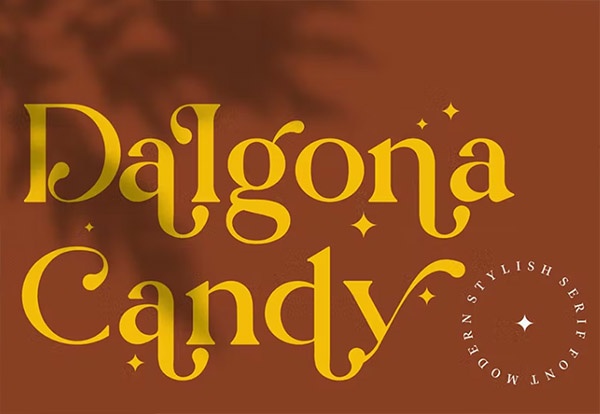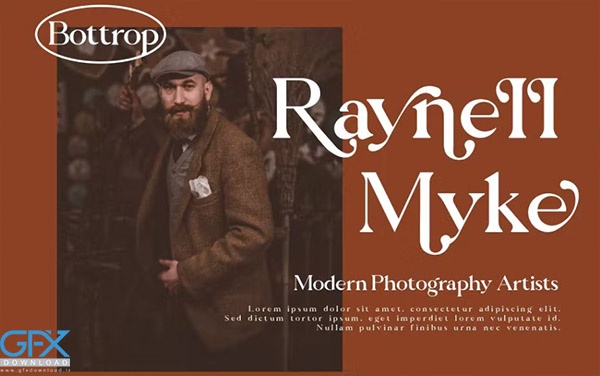
دانلود فونت رایگان آب نباتی Dalgona Candy
فونت آب نباتی Dalgona Candy
دانلود رایگان فونت انگلیسی آب نباتی Dalgona Candy
در این پست با معرفی یک فونت رایگان جدید با دست خط شیک و زیبا با شما همراه هستیم. دانلود فونت آب نباتی Dalgona Candy با حروف بزرگ، کوچک، اعداد و علائم نگارشی استاندارد ارائه شده است. همچنین شامل حروف کوچک Alternates، ligatures استاندارد، و swashes است.
دانلود رایگان فونت انگلیسی آب نباتی Dalgona Candy
فونت انگلیسی کلاسیک Dalgona Candy
کاملاً برای نقل قول های دست نویس، لوگو هایی به سبک امضا، دعوت نامه ها، پروژه های برندسازی شیک، و طرح های دست ساز محصولات و لوازم التحریر مناسب است.